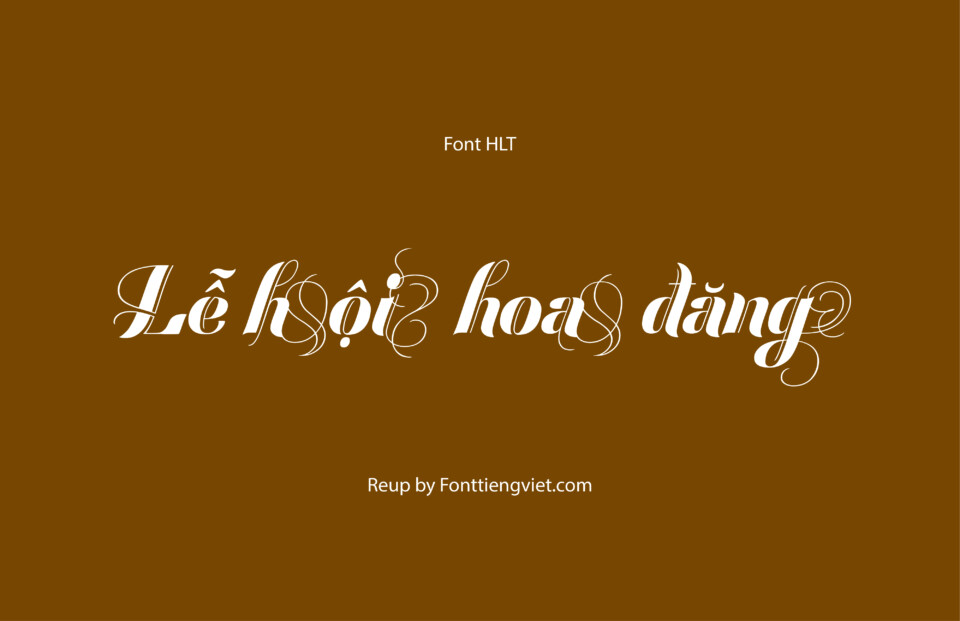
Tải Ngay Font Việt hóa HLT Festival Scrip tPro – Nét Chữ Bay Bổng Cho Mùa Lễ Hội
Giới thiệu về Font Việt hóa HLT Festival Scrip tPro
Trong thế giới thiết kế đồ họa, việc lựa chọn một Font Miễn Phí chất lượng luôn là ưu tiên hàng đầu của các bạn học sinh và thầy cô giáo. Font Việt hóa HLT Festival Scrip tPro là một bộ phông chữ nghệ thuật được chăm chút tỉ mỉ, mang phong cách viết tay uyển chuyển và hiện đại. Với bộ dấu tiếng Việt đầy đủ, bộ font này giúp người dùng dễ dàng tạo ra những ấn phẩm truyền thông đẹp mắt mà không lo lỗi font cơ bản.
Tại sao nên chọn Font Việt hóa HLT Festival Scrip tPro cho thiết kế?
Đặc điểm nổi bật của Font Việt hóa HLT Festival Scrip tPro chính là các đường nét thanh mảnh, uốn lượn tạo cảm giác vui tươi, đúng như tên gọi “Festival”. Đây là lựa chọn hoàn hảo để thiết kế thiệp chúc mừng, bìa báo tường, hay các slide bài giảng sáng tạo cho trường học. Sự linh hoạt trong cách kết nối các ký tự giúp văn bản trở nên sống động, gần gũi và đầy tính thẩm mỹ, phù hợp với mọi đối tượng yêu thích sự nhẹ nhàng.